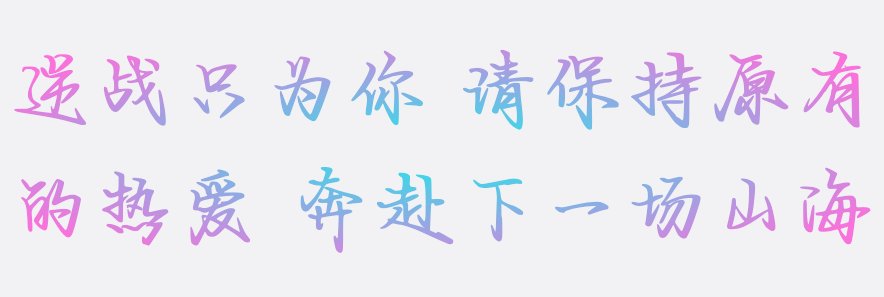
《逆战为你》以其独特的字形和连笔风格体现了书写的流畅感,同时又展现出端庄而又不失潇洒的特质。
这款字体不仅仅是一组字形,更是一种表达心灵深处思想和情感的工具。它以其连笔之间的和谐,勾画出每个字母之间深刻的联系,仿佛在述说着文字背后的故事。每一笔每一画都流畅而不失稳重,仿佛是一位优雅的舞者在纸上起舞。
更为重要的是,《逆战为你》传递着一种强烈的思想,即为你而战。这句简短而富有力量的口号激励着人们,教导我们要为自己的梦想、信仰和价值观而努力奋斗,无论面对何种逆境。这种坚定的信念贯穿于字体的每一笔,使得它不仅仅是一种书写方式,更是一种精神的象征。
《逆战为你》是一款令人陶醉的手写字体,它以其独特的字形和连笔风格,将书写提升到了一种艺术的层次。而其背后强大的思想,为我们提供了坚持不懈,为梦想奋斗的动力,正如字体所言,为你而战,永不止步。